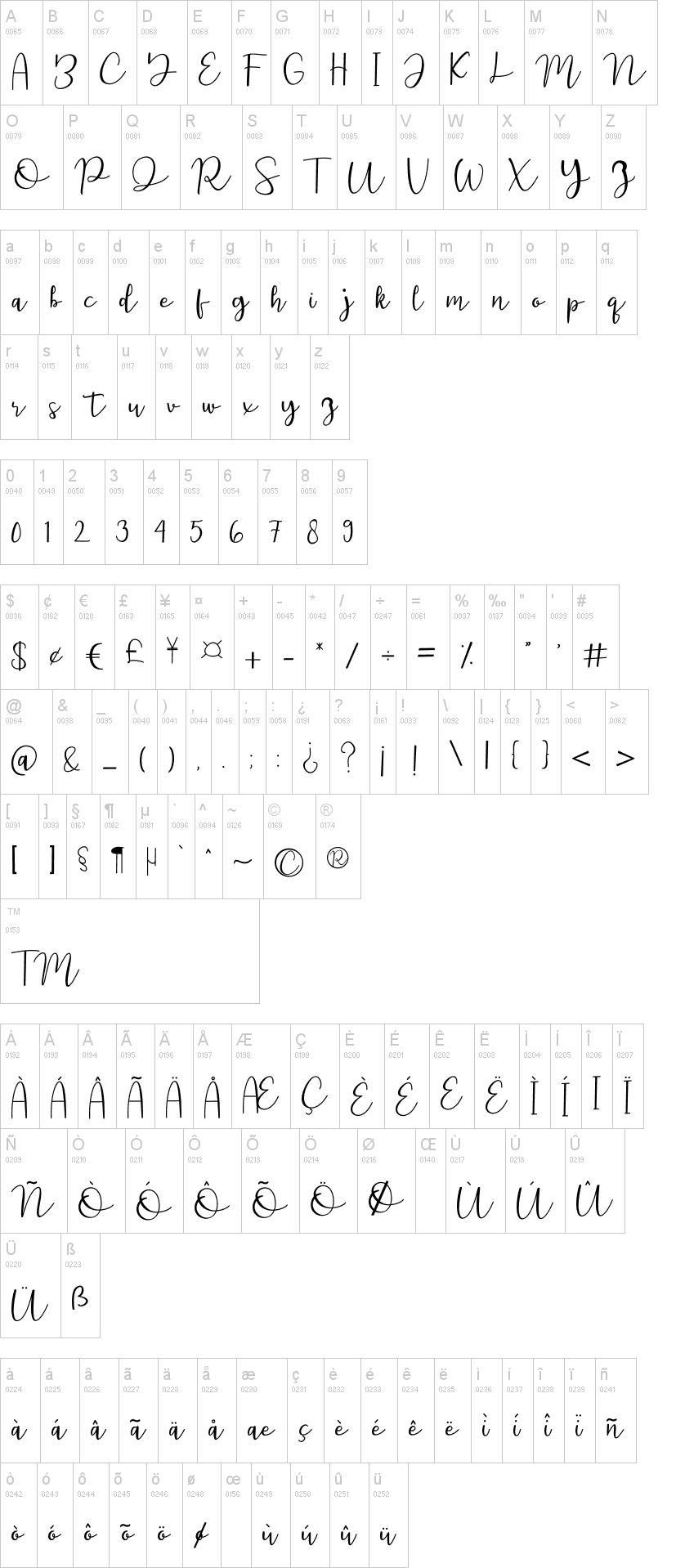
Featrisse 是一款精美的脚本字体,由字体设计师Miguel Reyes创作。它具有精致的笔画,流畅的线条,优雅的曲线,以及细腻的细节,给人一种温柔、精致的感觉。Featrisse 字体具有多种字体风格,可以用于报纸、杂志、书籍、海报、海报、展板等印刷品。它可以让你的设计作品充满活力,更加精致、优雅。内容介绍
Featrisse是一款非常不错的手写艺术字体,具有很好的视觉感,适合于文化类的宣传设计、商业类品牌的广告和产品包装设计以及个性化文字排版等较多场景。